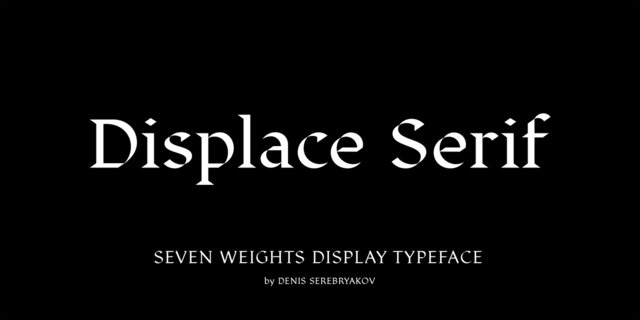
Displace Serif – это продолжение шрифта Displace. Добавление засечек позволяет увидеть этот шрифт по-новому. Создается отчетливое ощущение итальянского монументального шрифта, но более экспрессивного. Пропорции и размер засечек изменяются от начертания к начертанию и зависят от насыщенности, что позволяет шрифту иметь декоративный вид. В тонких начертаниях засечки деликатные, едва различимые, а в жирных – массивные. Броские и запоминающиеся шрифты этого семейства создают сильное эмоциональное впечатление и, несмотря на грубые модернистские формы, сохраняют классическую концепцию. Displace Serif подходит для дизайна печатных и электронных изданий. Шрифт разработал Денис Серебряков в 2019 году.
Ассоциации c начертанием Displace Serif BoldКачества и характер:
твердый, оригинальный, характерный, острый, резкий, четкий, серьезный, жесткий, железный, стальной, городской, устойчивый, необычный, гордый, динамичный, артистичный, дорогой, техничный, авторитетный, убедительный, важный, архитектурный, уверенный, экстравагантный, ровный, амбициозный, экспериментальный, выразительный, элитный, качественный, серебрянный, культурный, эстетичный, роскошный, драгоценный, отборный, богатый, звонкий, утонченный, модный, современный, музыкальный, стеклянный, эстетский, пафосный, солидный, пульсирующий, мерцающий